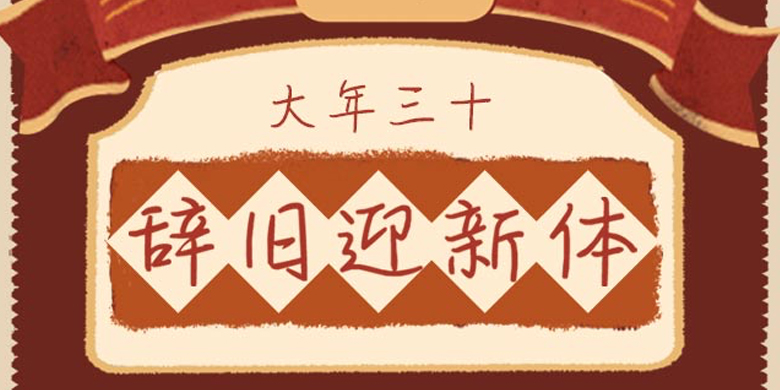
方正手迹-辞旧迎新体
字体品牌: 方正手迹 设计师:余丹 字体分类:常规书写·硬笔 字体属性:精品字 字符集:大陆简体(GB2312-80) 发布时间: 2020
辞旧迎新体这款字体字形偏扁,笔画柔中带刚,字里行间透出从容优雅。结构严谨,韵味十足。是一款极具个性的现代手写字体。适用于文艺类的书刊、品牌广告和产品包装设计,综艺影视用字,以及社交网络的个性化用字。